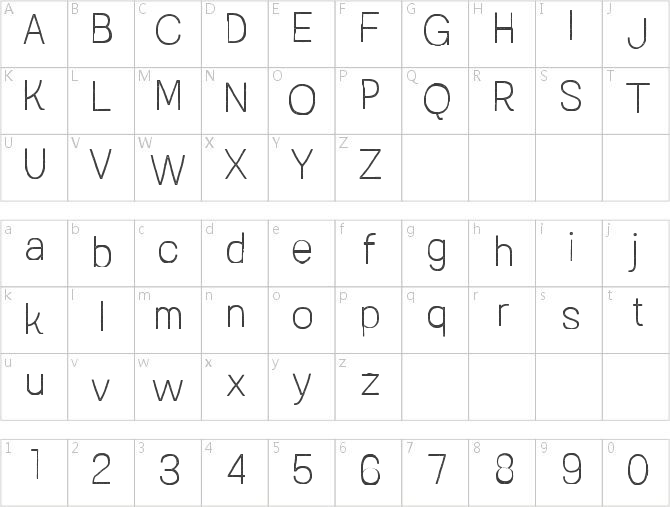
Austral Sans Stamp Thi
Austral Sans Stamp Thi介紹
Austral Sans Stamp Thi字體字庫是一款讓人賞心悅目、百看不厭的英文字體,適合各類廣告和產品包裝設計應用,字體大小1.66MB,格式為ttf字體,上傳用戶是釜源貿易,作者/版權方為未知